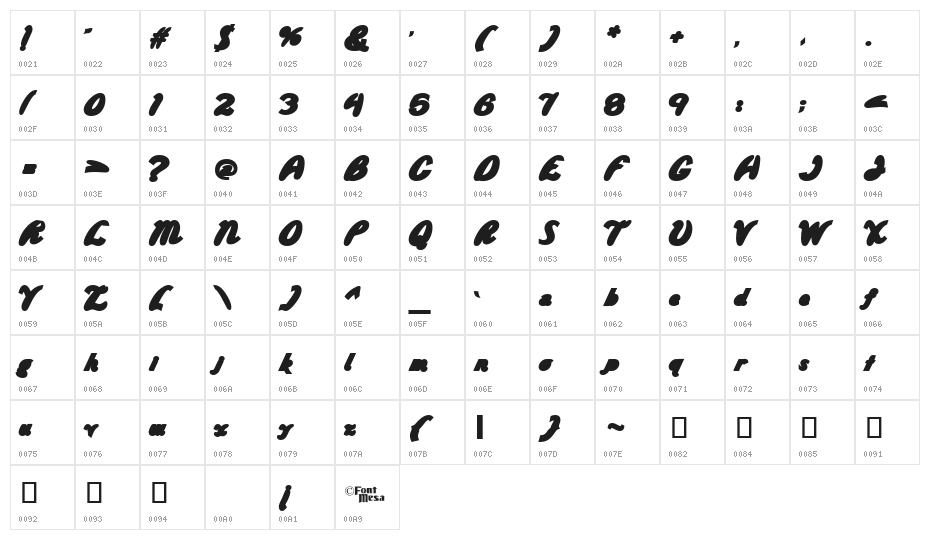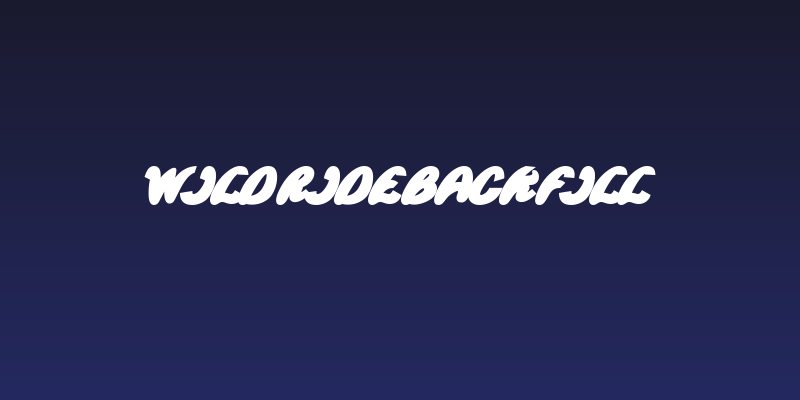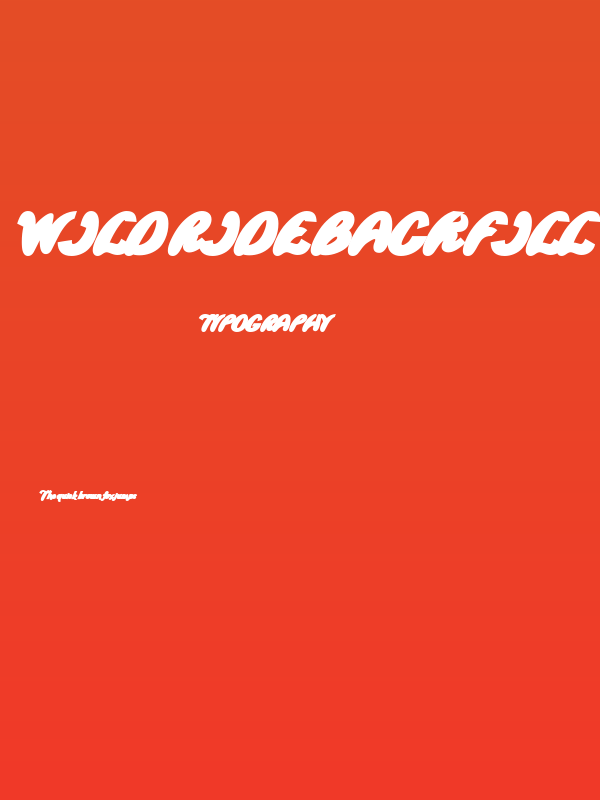
Wild Ride Back Fill Font
| Caso de uso | Logos, Headlines, Posters |
| Proyectos propuestos | Ideal for branding, logos, headlines, posters, and any design needing a bold, energetic script. |